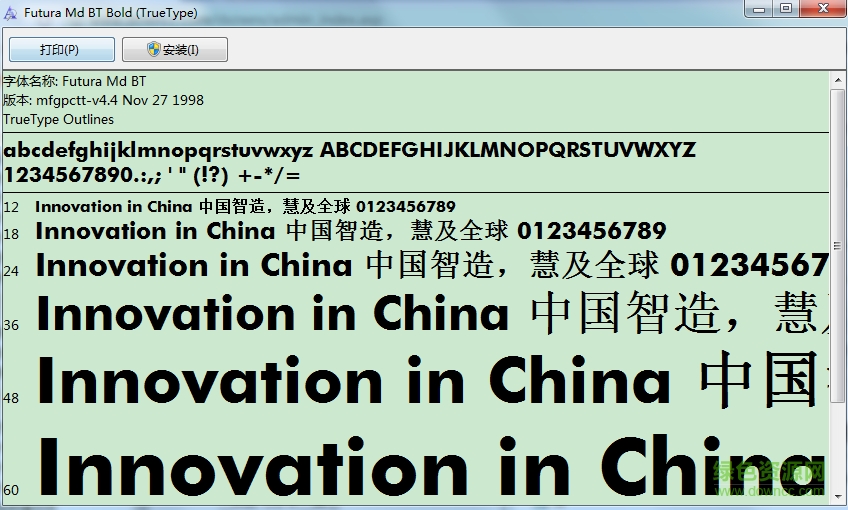
futura md bt bold是一款粗體英文字體,這款字體筆畫粗壯,整體效果非常出色,廣泛應用于排版印刷、廣告設(shè)計、標語等領(lǐng)域,歡迎需要的朋友來綠色資源網(wǎng)下載。
futura md bt bold字體字形端正大方,表現(xiàn)力強!常常用于廣告設(shè)計、宣傳文本、產(chǎn)品包裝等領(lǐng)域。